16 Font Panah Terbaik 2023 (Gratis & Premium)
Diterbitkan: 2023-10-17Pernahkah Anda kesulitan menemukan font yang sempurna untuk meningkatkan proyek desain grafis Anda? Tidak perlu mencari lagi! Dalam postingan blog kali ini, kami akan menampilkan 16 font panah terbaik yang dijamin akan meningkatkan desain proyek Anda.
Baik Anda sedang mengerjakan logo, poster, atau situs web, font panah ini akan menambahkan sentuhan gaya dan kecanggihan ekstra.
Pada artikel ini, kita akan mendalami dunia font panah dan menjelajahi fitur unik serta elemen desainnya. Kami juga akan membahas pentingnya memilih font yang tepat untuk proyek Anda dan bagaimana hal itu dapat berdampak signifikan terhadap estetika keseluruhan.
Dengan 16 font panah pilihan ini, Anda akan memiliki beragam opsi untuk dipilih, memastikan bahwa Anda menemukan yang paling cocok untuk kebutuhan desain spesifik Anda.
Jadi, bersiaplah untuk membawa proyek desain grafis Anda ke level berikutnya dengan font panah yang luar biasa ini. Baik Anda mencari sesuatu yang ramping dan modern atau berani dan menarik perhatian, kami siap membantu Anda.
Bersiaplah untuk menambahkan bakat dan kreativitas pada desain Anda saat kami menjelajahi 16 font panah terbaik yang tersedia. Ayo selami!
Font Panah Premium Terbaik
Ingin meningkatkan desain proyek Anda dengan beberapa font panah? Tidak perlu mencari lagi! Di bagian ini, kami telah memilih sendiri font panah premium terbaik yang pasti akan menambahkan sentuhan unik pada desain Anda. Jadi, silakan lihat font menakjubkan di bawah ini dan biarkan kreativitas Anda melambung!
Panah yang Digambar Tangan
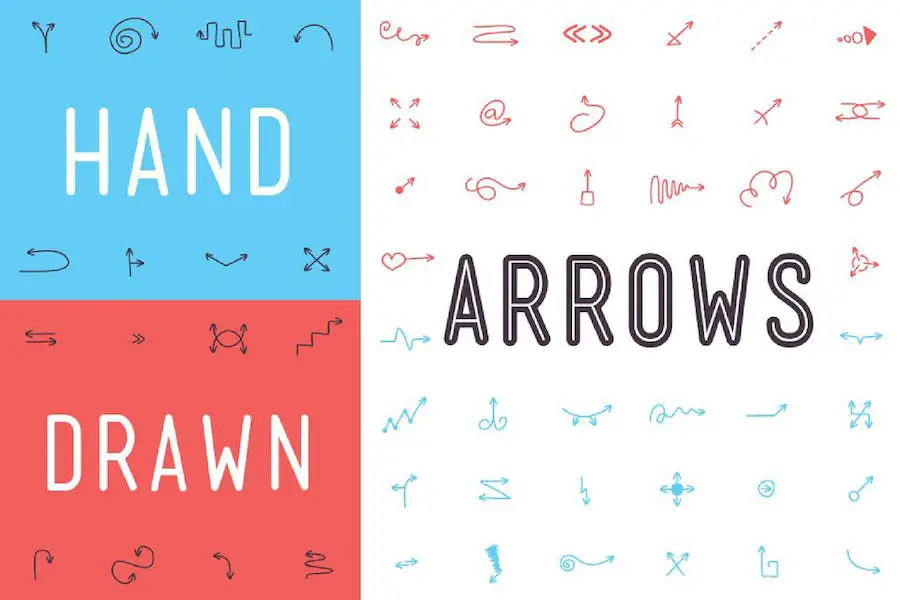
Panah Digambar Tangan adalah font dalam format .TTF yang menawarkan 98 panah unik yang digambar tangan, cocok untuk menyempurnakan proyek desain Anda. Panah ini dapat menambahkan sentuhan kreativitas dan keunikan pada desain Anda, menjadikannya menonjol dari yang lain.
Dengan 98 panah unik yang digambar tangan, font ini memberi Anda beragam pilihan untuk dipilih. Baik Anda mencari panah yang sederhana dan elegan atau desain yang lebih rumit dan menarik, Panah yang Digambar Tangan siap membantu Anda.
Setiap anak panah telah dibuat dengan cermat dengan nuansa gambar tangan, menambahkan sentuhan pribadi pada desain Anda.
Dengan memasukkan panah yang digambar tangan ini ke dalam proyek Anda, Anda dapat dengan mudah mengarahkan perhatian pemirsa dan menciptakan kesan gerakan.
Baik Anda mendesain logo, poster, situs web, atau bahkan grafik media sosial, panah ini dapat membantu Anda mengarahkan pandangan pemirsa dan menambah daya tarik visual pada desain Anda.
Garis Panah
Garis Panah adalah font lucu yang menambahkan sentuhan gaya kaligrafi pada proyek desain apa pun. Keindahannya terlihat pada undangan, kartu ucapan, materi branding, kartu nama, kutipan, poster, dan banyak lagi.
Dengan desainnya yang unik dan menawan, font ini pasti akan meningkatkan daya tarik proyek Anda secara keseluruhan.
Lengkungan yang memukau dan detail Garis Panah yang rumit menjadikannya pilihan yang menakjubkan bagi desainer mana pun. Gaya kaligrafinya menambah sentuhan keanggunan dan kecanggihan, membuat desain Anda menonjol dari yang lain.
Baik Anda sedang mengerjakan undangan pernikahan, grafik kutipan, atau kartu nama, font ini akan menghadirkan kesan keindahan dan keanggunan pada kreasi Anda.
Salah satu fitur menonjol dari Garis Panah adalah keserbagunaannya. Ini berpadu sempurna dengan berbagai elemen desain, melengkapi gaya atau tema apa pun yang Anda pikirkan.
Baik Anda menginginkan tampilan minimalis atau desain yang berani dan bersemangat, font ini dapat dengan mudah beradaptasi dengan visi Anda.
Panah Emas
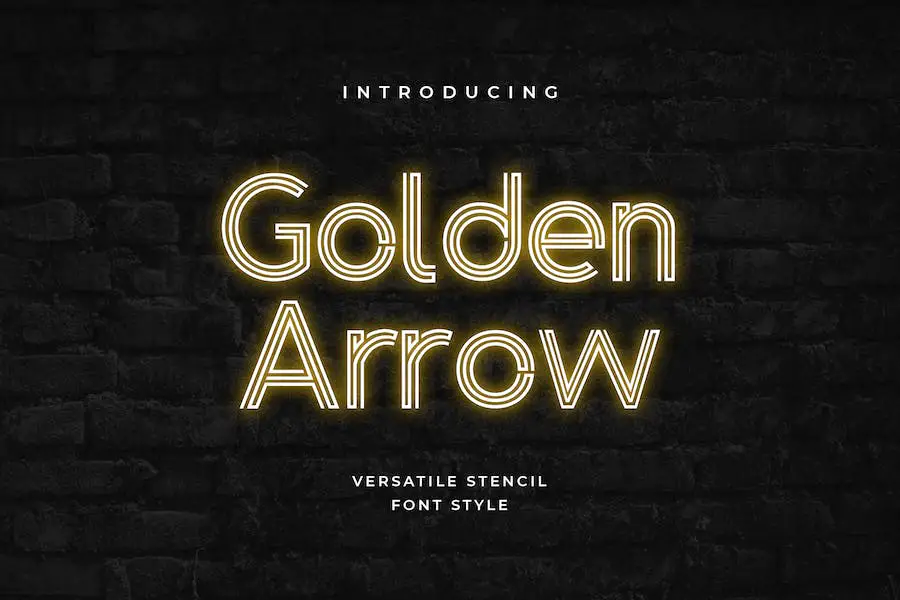
Font Golden Arrow adalah font geometris modern berkelas yang memadukan kurva lembut, garis lurus tajam, dan sudut lancip dengan indah. Ini adalah font yang sempurna untuk desainer grafis yang ingin menambahkan sentuhan kecanggihan dan keanggunan pada proyek mereka.
Dengan desainnya yang unik, font ini pasti akan meningkatkan estetika desain apa pun secara keseluruhan.
Atribut font Golden Arrow membuatnya menonjol dari font lain yang tersedia. Kombinasi kurva lembut dan sudut tajam menciptakan kontras visual yang menarik yang dapat membantu menarik perhatian ke elemen tertentu dalam sebuah desain.
Baik itu untuk logo, website, atau proyek desain lainnya, font ini akan menambah sentuhan elegan dan profesionalisme.
Salah satu keunggulan font Golden Arrow adalah keserbagunaannya. Ini dapat digunakan untuk judul besar dan teks lebih kecil, sehingga cocok untuk berbagai aplikasi desain.
Baik Anda sedang mengerjakan proyek cetak atau desain digital, font ini akan beradaptasi dengan indah dengan ukuran atau format apa pun.
Urbanisme Hantu
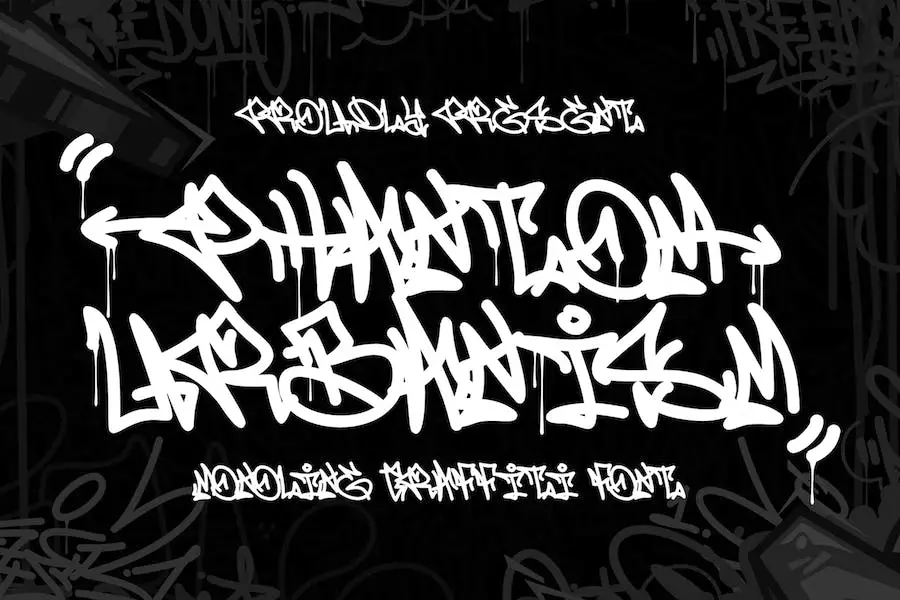
Phantom Urbanism adalah font monoline fantastis yang menghadirkan sentuhan grafiti perkotaan pada proyek Anda. Dengan efek panahnya yang bergaya, font ini menambah kedalaman dan dekorasi, menjadikannya pilihan sempurna bagi desainer grafis yang ingin menyempurnakan desain mereka.
Baik Anda sedang mengerjakan logo, poster, atau situs web, Phantom Urbanism akan menambah kesan unik dan edgy pada karya Anda.
Gaya font monoline ini memberikan tampilan yang ramping dan modern, sedangkan tema grafiti menambah kesan pemberontak dan urban. Namun yang membuat Phantom Urbanism benar-benar menonjol adalah rangkaian gayanya dengan efek panah.
Fitur khusus ini memungkinkan Anda memasukkan panah secara mulus ke dalam desain Anda, menciptakan elemen menarik yang menarik perhatian dan memandu pandangan pemirsa.
Jetsy
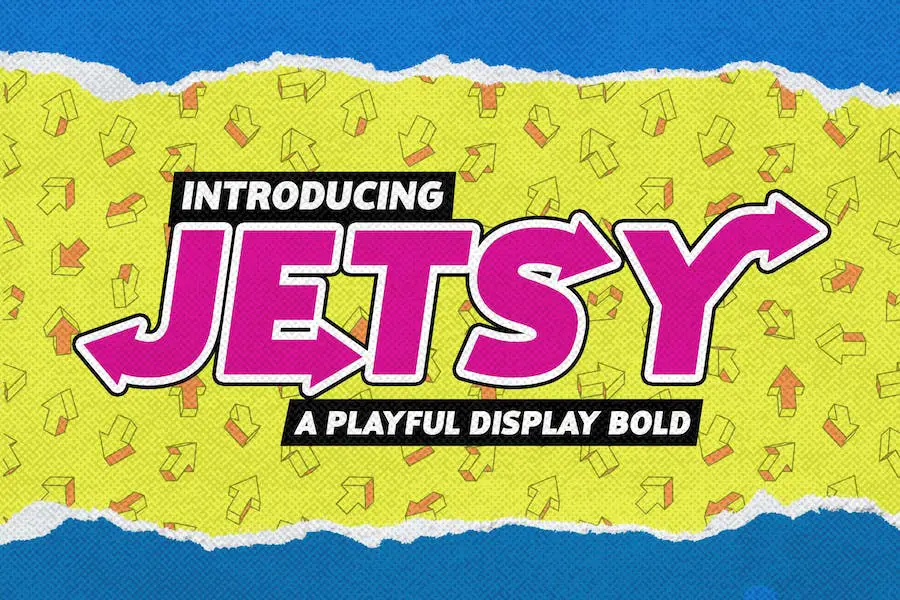
Jetsy adalah font Playful Display Bold San Serif yang dibuat oleh studio Drizy. Font ini sangat cocok untuk desainer grafis yang ingin menambahkan sentuhan kreativitas dan keceriaan pada proyek mereka. Dengan gayanya yang berani dan eye-catching, Jetsty pasti akan membuat desain Anda menonjol.
Font ini menawarkan semua gaya dasar yang Anda perlukan untuk proyek yang sukses, termasuk huruf besar dan kecil, angka, dan karakter khusus. Baik Anda sedang mengerjakan logo, poster, atau desain lainnya, Jetsty siap membantu Anda.
Dengan bentuk seperti panah dan desain yang terinspirasi grafiti, Jetsty adalah pilihan tepat untuk proyek yang membutuhkan tampilan berani dan edgy. Ini adalah font serbaguna yang dapat digunakan untuk berbagai tujuan, mulai dari branding, periklanan, hingga grafik media sosial.
Jika Anda seorang desainer grafis yang ingin menambahkan gaya pada desain Anda, Jetsty layak untuk dipertimbangkan. Gayanya yang ceria dan berani akan membantu proyek Anda menonjol dari yang lain. Cobalah dan lihat perbedaannya pada karya desain Anda.
RNS Mil
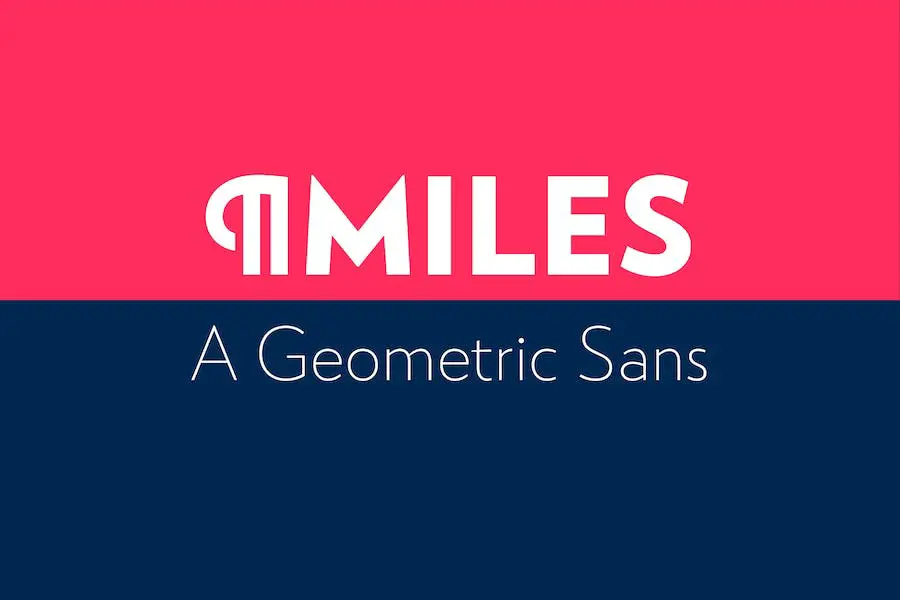
Keluarga font RNS Miles adalah font unik dan serbaguna yang menggabungkan bentuk geometris, bentuk terbuka, dan sedikit gaya aneh. Hal ini bertujuan untuk menciptakan desain yang harmonis, netral, dan kontras rendah untuk berbagai proyek.
Dengan bentuk geometrisnya, RNS Miles menawarkan estetika ramping dan modern yang dapat menonjolkan desain apa pun. Baik Anda sedang mengerjakan logo, poster, atau tata letak situs web, rangkaian font ini memiliki fleksibilitas untuk disesuaikan dengan proyek Anda.
Bentuk RNS Miles yang terbuka menciptakan kesan lapang dan lancar dalam desain. Hal ini memungkinkan keterbacaan mudah dan memastikan bahwa pesan Anda tersampaikan dengan mudah kepada audiens Anda.
Menambahkan sentuhan suasana hati yang aneh, RNS Miles menambahkan elemen intrik dan keunikan yang halus pada desain Anda. Ini membantu proyek Anda menonjol dari yang lain sambil mempertahankan rasa profesionalisme dan kecanggihan.
salah ketik
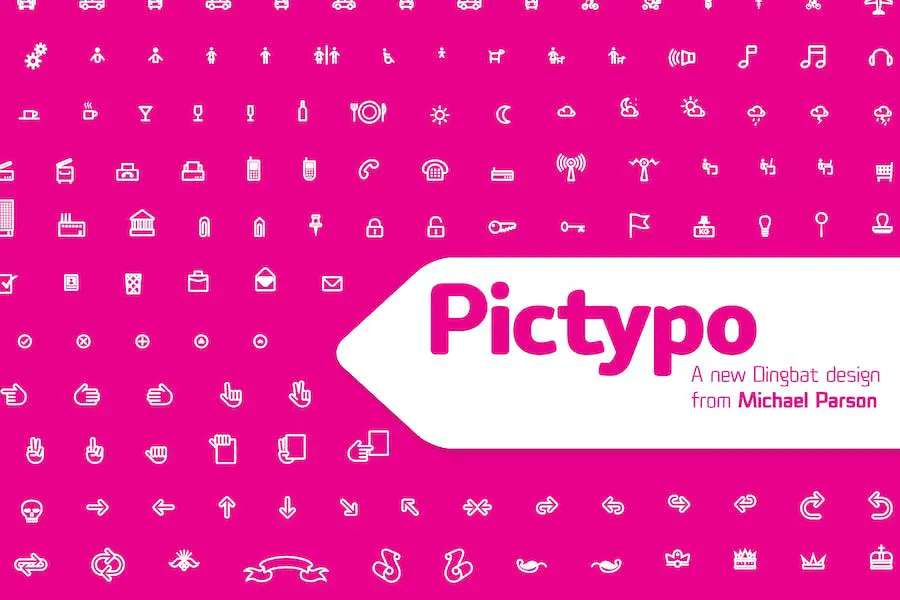
Pictypo adalah sekumpulan font dingbat yang menghadirkan sentuhan fungsional dan gaya pada desain Anda. Dengan gayanya yang terbuka dan membulat, ia menawarkan beragam koleksi simbol, termasuk panah, ikon cuaca, ikon kantor, dan bahkan kendaraan mobilitas.
Fleksibilitas Pictypo menjadikannya suatu keharusan bagi desainer grafis yang ingin menyempurnakan proyek mereka dengan simbol yang menarik.
Baik Anda memerlukan panah untuk memandu perhatian pemirsa atau ikon cuaca untuk menambahkan konteks, kumpulan font ini siap membantu Anda. Ditambah lagi, gaya bulat menambah kesan modern dan ramah pada desain Anda.
Tapi itu tidak berhenti di situ. Pictypo melampaui simbol biasa dan menawarkan berbagai ikon yang berkaitan dengan kehidupan kantor.
Dari perlengkapan kantor sederhana hingga simbol yang lebih spesifik seperti layar komputer atau bahkan cangkir kopi, Anda akan menemukan semua yang Anda butuhkan untuk membuat grafik yang menarik secara visual dan relevan untuk proyek perusahaan.
Kombinasi
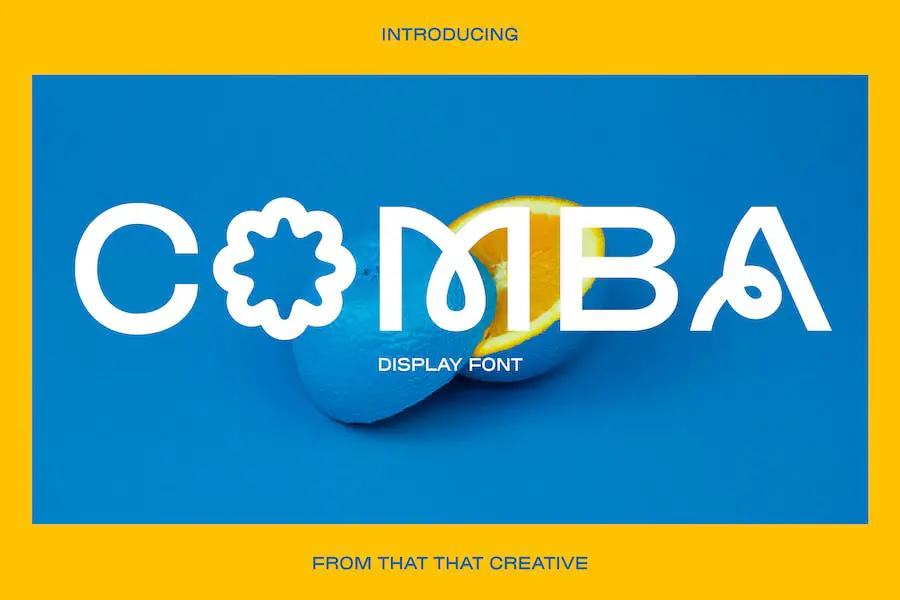
Comba adalah font tampilan huruf besar semua yang luar biasa yang ideal untuk jenis tampilan dan branding modern. Dengan huruf-hurufnya yang unik dan menawan, menarik perhatian pembaca dan membuat mereka tersenyum.
Font ini sangat cocok untuk desainer grafis yang ingin menyempurnakan proyek mereka dan menciptakan pengalaman visual yang mengesankan.
Baik Anda sedang mengerjakan logo, desain kemasan, atau proyek kreatif lainnya, Comba akan menambahkan sentuhan ekstra kepribadian dan pesona. Keserbagunaan dan daya tariknya yang menarik menjadikannya font yang wajib dimiliki untuk perangkat desainer mana pun.
Grafika
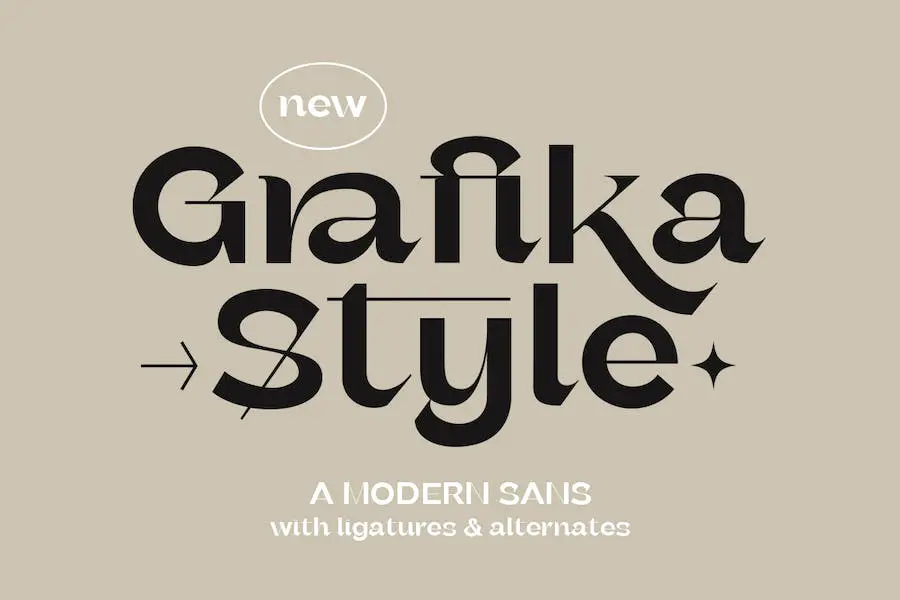
Grafika adalah font sans modern bernama 'It' yang dilengkapi dengan ligatur dan alternatif. Ini sempurna untuk desainer grafis yang ingin menyempurnakan desain proyek mereka dengan font grafiti panah.
Dengan Grafika, Anda mendapatkan font bergaya dan kontemporer yang menambahkan sentuhan unik pada desain Anda. Ini menawarkan ligatur dan alternatif, memungkinkan Anda membuat tipografi khusus dan menarik.
Baik Anda sedang mengerjakan situs web, logo, atau proyek desain lainnya, Grafika dapat meningkatkan pekerjaan Anda ke level berikutnya.
Font ini memiliki tampilan yang bersih dan modern, menjadikannya serbaguna dan cocok untuk berbagai gaya desain. Gaya grafiti panahnya menambahkan elemen ceria dan tegang pada proyek Anda, cocok untuk menambahkan kepribadian dan daya tarik visual.
KAMU
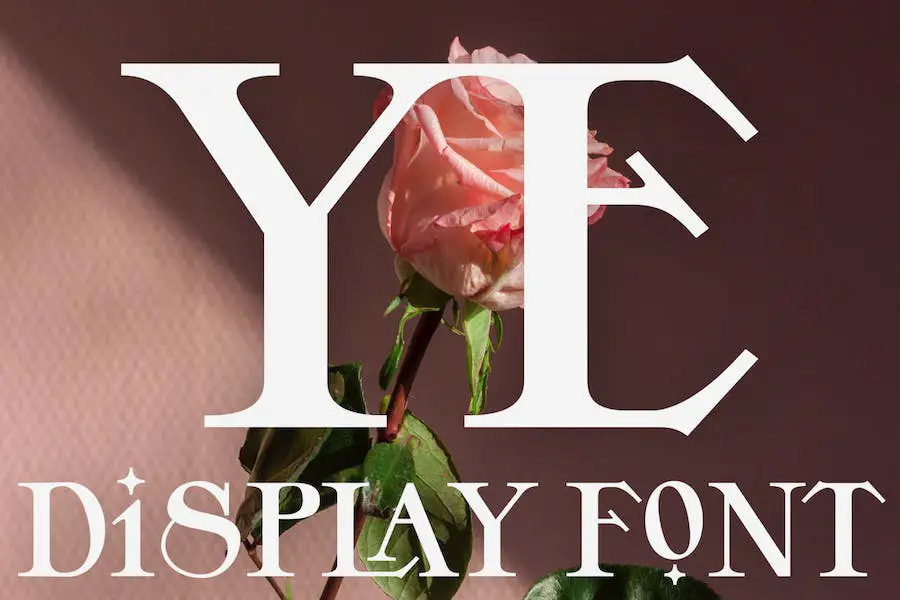
Memperkenalkan YE, jenis huruf tampilan Serif yang berani dan kontemporer yang akan membawa desain Anda ke level berikutnya.
Dengan gaya semi-kondensasi, pusat visual yang tinggi, dan serif bersudut tajam, font ini sangat cocok untuk desainer grafis yang ingin meningkatkan desain proyek mereka.
Fitur menonjol dari YE adalah keanggunan dan kekuatannya, menjadikannya pilihan sempurna untuk desain apa pun yang memerlukan pernyataan berani.
Selain itu, ia mencakup lebih dari 50 pengikat dan alternatif untuk memberi Anda lebih banyak kemungkinan kreatif. Dengan YE, desain Anda tidak akan sama lagi.
Cinta Cupid
Cupid Love adalah tampilan jenis huruf yang berani dan menyenangkan, cocok untuk menambahkan sentuhan indah pada proyek Hari Valentine Anda.
Dengan gaya teratur dan karakter bergantian yang menampilkan panah dewa asmara, jenis huruf ini sangat bagus untuk berbagai aplikasi seperti barang dagangan, percetakan, kutipan, kartu, poster, dan banyak lagi.
Ini menambahkan kesan ceria dan romantis pada desain Anda, menjadikannya menonjol dan menangkap esensi cinta.
Baik Anda seorang desainer grafis yang mengerjakan proyek bertema Hari Valentine atau sekadar ingin menghadirkan sentuhan romantis pada desain Anda, Cupid Love adalah font yang wajib dimiliki yang akan menyempurnakan keseluruhan tampilan dan nuansa karya Anda.
Font Panah Gratis Terbaik
Jika Anda seorang desainer grafis yang mencari font untuk menyempurnakan desain proyek Anda, Anda telah datang ke tempat yang tepat. Di bagian artikel ini, kami akan menampilkan font panah gratis terbaik yang dapat menambahkan sentuhan gaya dan kreativitas pada desain Anda.
Teruslah membaca untuk menemukan font luar biasa ini dan tingkatkan permainan desain Anda!
panah
Arrows oleh Aisyah adalah font luar biasa yang sempurna untuk desainer grafis yang ingin menyempurnakan desain proyek mereka. Font gratis ini menawarkan berbagai macam desain panah yang dapat menambahkan elemen gaya dan menarik pada desain apa pun.
Dengan gayanya yang mudah dibaca dan sentuhan pribadinya, Arrows wajib dimiliki oleh koleksi desainer mana pun.
Yang membedakan Arrows adalah keserbagunaannya. Baik Anda sedang mengerjakan logo, situs web, atau desain cetak, font ini memiliki desain panah yang sempurna untuk memenuhi kebutuhan Anda. Dari panah sederhana dan minimalis hingga panah rumit dan dekoratif, selalu ada sesuatu untuk semua orang.
Font ini hadir dalam berbagai bobot, memungkinkan Anda bereksperimen dan menemukan keseimbangan yang tepat untuk desain Anda.
Fitur hebat lainnya dari Arrows adalah kemudahan penggunaannya. Font ini ramah pengguna dan mudah diakses, membuatnya mudah untuk dimasukkan ke dalam proyek Anda.
Selain itu, dengan lisensi penggunaan pribadi gratis, Anda dapat menikmati manfaat font ini tanpa khawatir melanggar undang-undang hak cipta apa pun.
Manusia panah
Arrowman adalah font yang dibuat oleh Ahmad Zulfikar Ali dan tersedia untuk penggunaan pribadi tanpa biaya. Font ini dirancang khusus untuk desainer grafis yang ingin menyempurnakan desain proyek mereka dengan tipografi panah yang unik dan menarik.
Dengan Arrowman, Anda dapat menambahkan sentuhan kreativitas dan daya tarik visual pada desain Anda tanpa biaya tambahan. Jadi, mari jelajahi atribut font ini dan lihat bagaimana font ini dapat meningkatkan proyek Anda.
Arrowman adalah font yang sangat serbaguna yang menawarkan beragam desain panah. Apakah Anda memerlukan panah yang sederhana dan ramping atau yang lebih rumit dan dekoratif, font ini siap membantu Anda.
Variasi gaya panah memungkinkan Anda menemukan pasangan yang cocok untuk proyek Anda, baik itu logo, desain situs web, atau grafik lainnya.
Salah satu kelebihan Arrowman adalah kemudahan penggunaannya. Ini kompatibel dengan berbagai perangkat lunak desain, sehingga memudahkan desainer grafis untuk mengintegrasikannya ke dalam proyek mereka dengan lancar.
Jadi, apakah Anda menggunakan Adobe Photoshop, Illustrator, atau perangkat lunak desain lainnya, Anda dapat dengan mudah memasukkan Arrowman ke dalam desain Anda tanpa kesulitan.
Nona Panah
Miss Arrow oleh Bearytype adalah font fantastis untuk desainer grafis yang ingin menyempurnakan desain proyek mereka. Font panah ini menambahkan sentuhan unik dan bergaya pada desain apa pun, menjadikannya sempurna untuk menciptakan visual yang menarik.
Dengan Miss Arrow, Anda memiliki kebebasan menggunakannya untuk proyek pribadi tanpa biaya apa pun. Ini berarti Anda dapat bereksperimen dan memasukkan font ini ke dalam karya Anda tanpa mengeluarkan banyak uang.
Atribut Miss Arrow inilah yang membuatnya menonjol dari font panah lain yang tersedia. Desainnya yang ramping dan dibuat dengan baik memastikan bahwa desain Anda akan memiliki tampilan yang halus dan profesional.
Anak panah dirancang dengan cermat dan dibentuk dengan indah, menjadikannya menarik secara visual dan menarik perhatian.
Panah Liar
Wild Arrows adalah font serbaguna yang sempurna untuk desainer grafis yang ingin menyempurnakan proyek mereka dengan sentuhan kreativitas. Dibuat oleh BamWithSpam, font ini menghadirkan elemen unik dan dinamis pada desain apa pun.
Dengan Wild Arrows, Anda dapat menambahkan fitur menarik ke proyek Anda. Font ini menyertakan serangkaian simbol panah yang dapat digunakan untuk menekankan elemen penting atau membuat efek visual yang menarik.
Baik Anda mendesain poster, situs web, logo, atau Wild Arrows memberi Anda fleksibilitas untuk bermain dengan gaya berbeda dan menciptakan desain yang menawan.
Salah satu atribut utama Wild Arrows adalah variasinya. Font ini menawarkan beragam desain panah, dari yang sederhana dan elegan hingga tebal dan rumit.
Dengan beragam pilihan, Anda dapat dengan mudah menemukan panah yang sempurna untuk disesuaikan dengan warna dan gaya desain Anda. Variasi ini memungkinkan Anda bereksperimen dan membuat proyek yang benar-benar unik dan menakjubkan secara visual.
Panah PW
PW Arrow oleh Peax Webdesign adalah font fantastis yang dirancang khusus untuk desainer grafis. Font ini sangat cocok untuk menambahkan sentuhan gaya dan unik pada desain proyek apa pun. Dengan desainnya yang terinspirasi panah, ia menghadirkan kesan gerakan dan arah pada karya seni Anda.
Salah satu atribut menonjol dari PW Arrow adalah keserbagunaannya. Baik Anda perlu membuat logo yang menarik, header situs web yang menarik, atau grafik media sosial yang menawan, font ini siap membantu Anda.
Ini menawarkan berbagai macam desain panah, memungkinkan Anda bereksperimen dan menemukan yang paling cocok untuk proyek Anda.
PW Arrow tidak hanya unggul dalam desain, tetapi juga memberikan fungsionalitas. Fontnya dibuat dengan baik, memastikan garis halus dan tajam dalam ukuran atau format apa pun. Ini kompatibel dengan perangkat lunak desain populer, membuatnya mudah untuk diintegrasikan ke dalam alur kerja Anda yang ada.
Pertanyaan yang Sering Diajukan
Font panah adalah tipografi yang menampilkan berbagai simbol atau ikon panah sebagai karakter. Panah ini dapat digunakan untuk menambahkan daya tarik visual dan arah pada proyek teks atau desain.
Ya, banyak font panah tersedia untuk penggunaan komersial. Namun, penting untuk memeriksa persyaratan lisensi setiap font tertentu sebelum memasukkannya ke dalam proyek komersial Anda.
Beberapa font mungkin memerlukan atribusi atau memiliki batasan, jadi sebaiknya tinjau informasi lisensi yang disediakan oleh pembuat font atau situs web.
Menggunakan font panah dapat meningkatkan keseluruhan tampilan dan efektivitas desain Anda. Mereka dapat membantu mengarahkan perhatian pemirsa, menunjukkan arah atau gerakan, dan menambahkan elemen visual yang unik.
Dengan memasukkan font panah ke dalam desain Anda, Anda dapat dengan mudah menyampaikan pesan atau menciptakan kesan mengalir dan navigasi.
Kesimpulan
Sebagai kesimpulan, kami telah menjelajahi 16 font panah terbaik yang dapat digunakan desainer grafis untuk menyempurnakan desain proyek mereka. Kita telah membahas fitur unik setiap font dan bagaimana font tersebut dapat menambahkan sentuhan gaya pada desain apa pun.